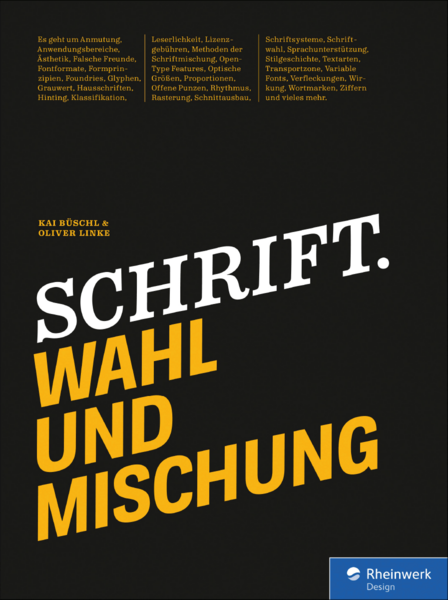
Nach dem ABC der Typografie erschien in der Designsparte des »Rheinwerk Verlages« ein weiteres umfangreiches Typografie-Buch. Die Autoren Kai Büschl und Oliver Linke erklären auf knapp 400 zweifarbigen Seiten wie man Schriften auswählt und mischt.
Den zwei Kapiteln zu Schriftwahl und -mischung sind ganze vier Kapitel mit Grundlagen vorangestellt:
- »Schrift formal betrachten« mit Einführungen zur Entwicklung der lateinischen Schrift, Schriftstilen und -schnitten, Klassifikationsmöglichkeiten usw.
- »Schrift technisch verstehen« mit Hinweisen zu digitalen Fonts, Fontformaten, Glyphen, OpenType, Variable Fonts usw.
- »Schrift funktional beleuchtet« mit Erklärungen zum Prozess des Lesens und der Rolle von Lesbarkeit und Leserlichkeit.
- »Schrift beurteilen« mit Hinweisen zu Schnitt- und Zeichenausbau, Schriftqualität usw.
Im fünften Kapital kommen wir dann zum Kern des Buches. Die Autoren gruppieren Schriftanwendungen in 15 Gruppen – von grundsätzlichen Unterteilungen wie »lineares Lesen« und »Akzidenztypografie« bis hin zu Spezialbereichen wie Signaletik, Kartografie, und mathematischer Satz. Jede Gruppe wird dann besprochen und in ein tabellarisches Anforderungsprofil überführt. Daraus lässt sich dann leicht ablesen, welche Kriterien relevant sind und welche vielleicht nicht. Satzbeispiele und Abbildungen von Drucksachen erklären die jeweilige Anwendung zudem visuell.
Es folgen knapp 40 Seiten mit ausführlichen Erklärungen zu Strategien der Schriftmischung. Kapitel 7 und 8 bilden dann noch eine Art Bonus mit zusätzlichen vermischten Informationen etwa zu Custom Fonts, Schriftanbietern und zur Schriftlizenzierung.
Fazit:
Grundsätzliche finde ich es weiterhin schade, dass sich Typografie-Bücher so selten ergänzen und die einführenden Informationen in jedem Typografie-Buch erneut wiederholt werden. Ich würde zum Beispiel lieber jeweils ein gutes Experten-Buch zur Entwicklung der lateinischen Schrift und zum Lesen aus wissenschaftlicher Sicht empfehlen, statt die verkürzten Überblicke in ähnlicher Weise in jedem Typografie-Buch wieder vorzufinden.
Wo das Buch dann jedoch brilliert ist der eigentlicher Kern, der sich tatsächlich mit der Schriftwahl und Mischung auseinandersetzt. Die Umsetzung über einen einheitlichen Anforderungskatalog macht die Sache übersichtlich und leicht verständlich. Insbesondere angehende professionelle Gestalter bekommen hier ein praxisnahes Werkzeug an die Hand. Das ebenfalls kürzlich vorgestellte Buch Schriftypen Verstehen Kombinieren ist im Vergleich deutlich akademischer angelegt.
Bei den technischen Erklärungen macht es sich übrigens bezahlt, dass die Autoren nicht nur Schriftanwender sind, sondern auch selbst Schriftgestalter. Hier wird dann entsprechend mehr erklärt als in vergleichbaren Büchern und auch neuere technischen Entwicklungen sind bereits berücksichtigt.
Auffällig gelungen ist auch das Layout das recht großformatigen Hardcover-Buches. Die Möglichkeiten der Schriftmischung und der verschiedenen Anwendungsbereiche (Überschriften, gut lesbare Fließtexte, Bildunterschriften usw.) werden hier perfekt und überzeugend vorgeführt.
Beim anfangs erwähnten Buch »ABC der Typografie« aus dem gleichen Verlag hatte ich noch betont, dass die Texte eher nüchtern und sachlich geschrieben sind. Das hier vorliegende Buch marschiert in die entgegengesetzte Richtung. Politische Bemerkungen, Wertungen und Empfehlungen ziehen sich durch das ganze Buch. Und es spricht freilich nichts dagegen, für die eigenen Werte einzustehen. Der so entstandenen Mischung aus Fachinformationen und Politik stehe ich allerdings eher kritisch gegenüber, da es für die Leser schlicht schwer zu trennen sein wird, ob bestimmte Aussagen nun typografisches Wissen oder politisch motivierte Behauptungen sind.